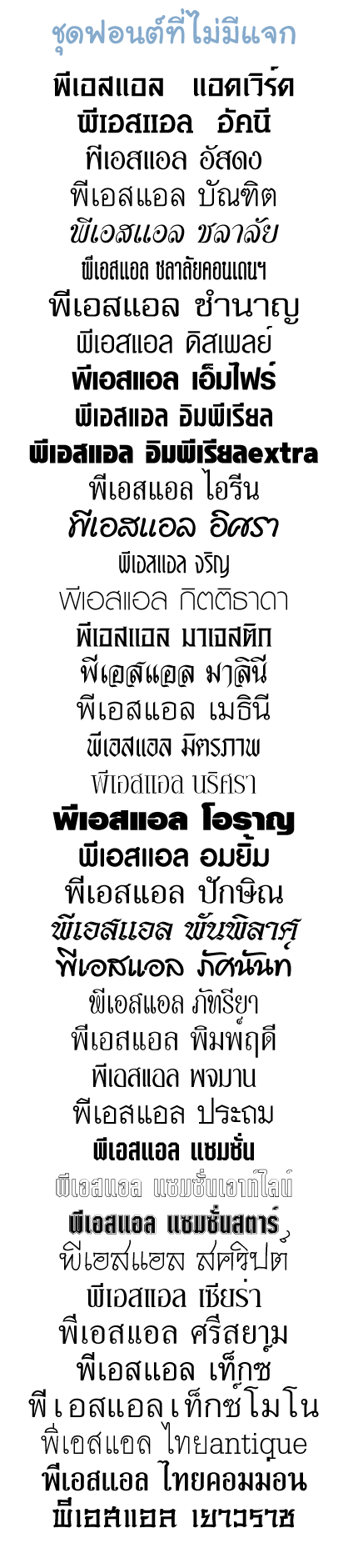
ต้องการฟ้อนของ Magazine ทั้วไป
อยากได้ฟ้อนแบบของ Magazine ทั่วไปอะครับ ที่ผมเป็นส่วนมากมันเป็นฟ้อนที่ไม่มีหัว ตัวบางๆ คล้ายๆกับฟ้อน lily อะครับ แต่มันบางกว่าเยอะ แล้วก็สวยกว่าด้วย
scan ตัวอย่างให้ดูหน่อยครับ
แมกกาซีนทั่วไปแถวไหนครับ
พวกแมกกาซีนไก่ชน หรือพระเครื่อง  :09:
อ๋อ... ถ้าเป็นกิติธาดาละก็.....